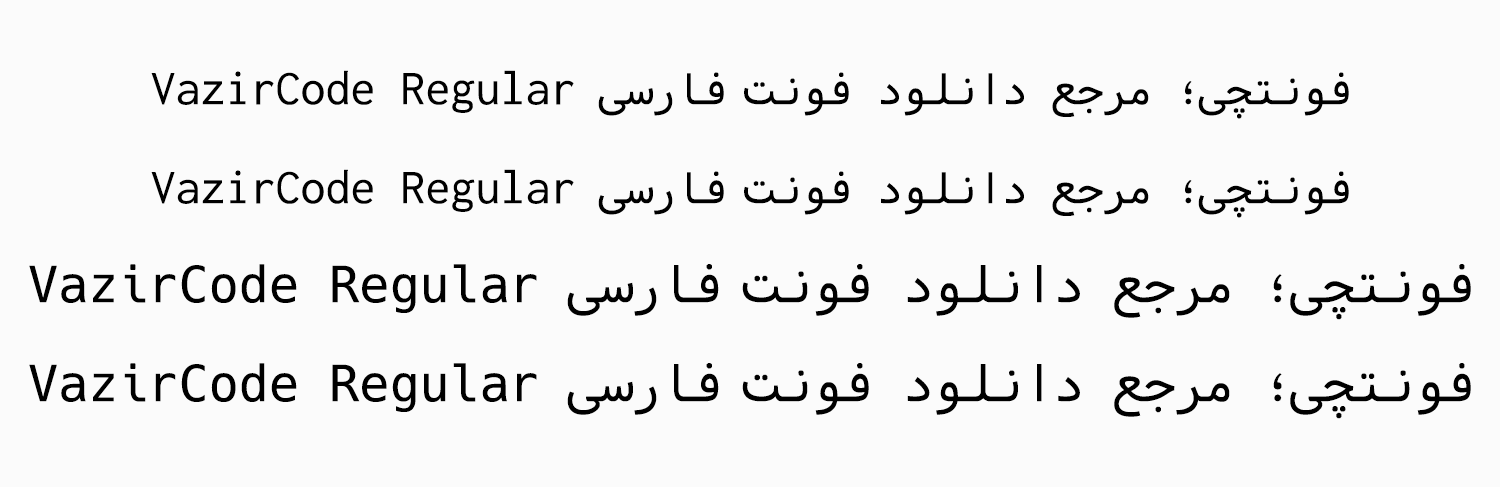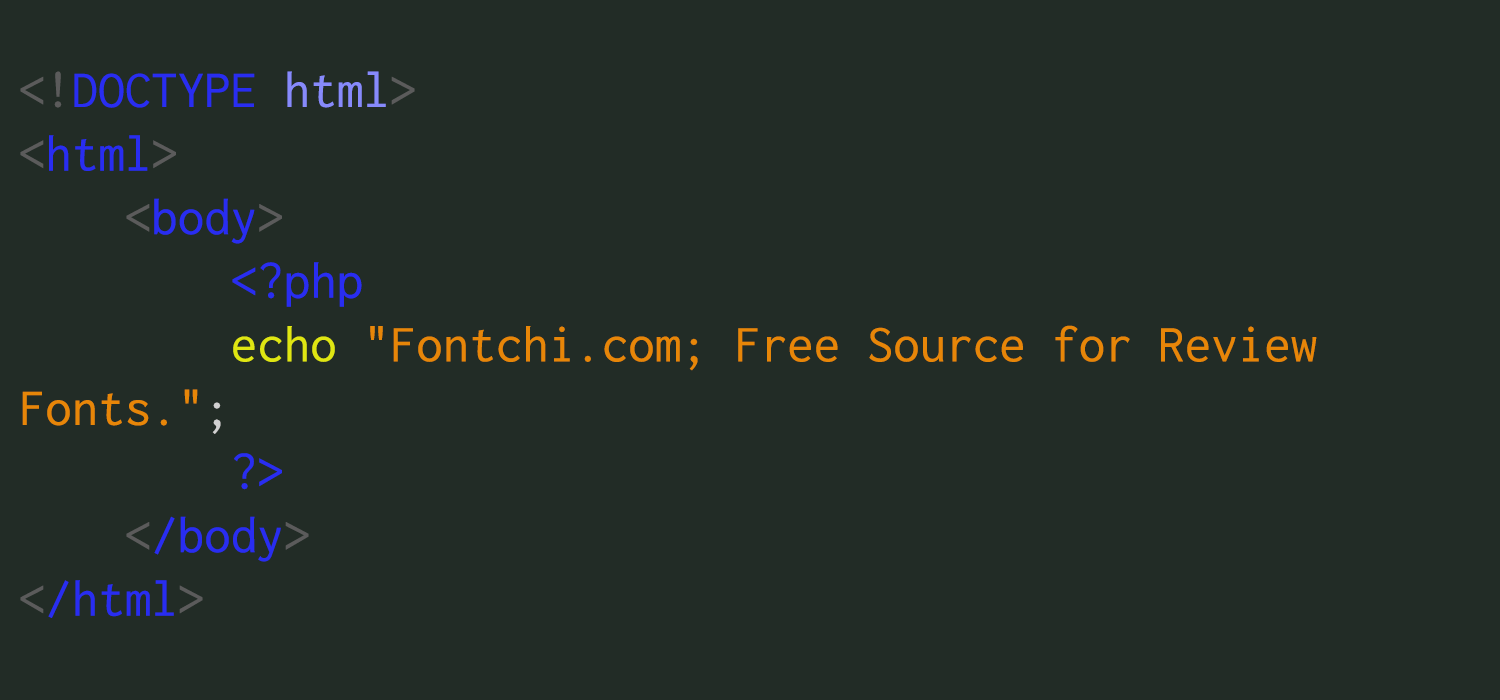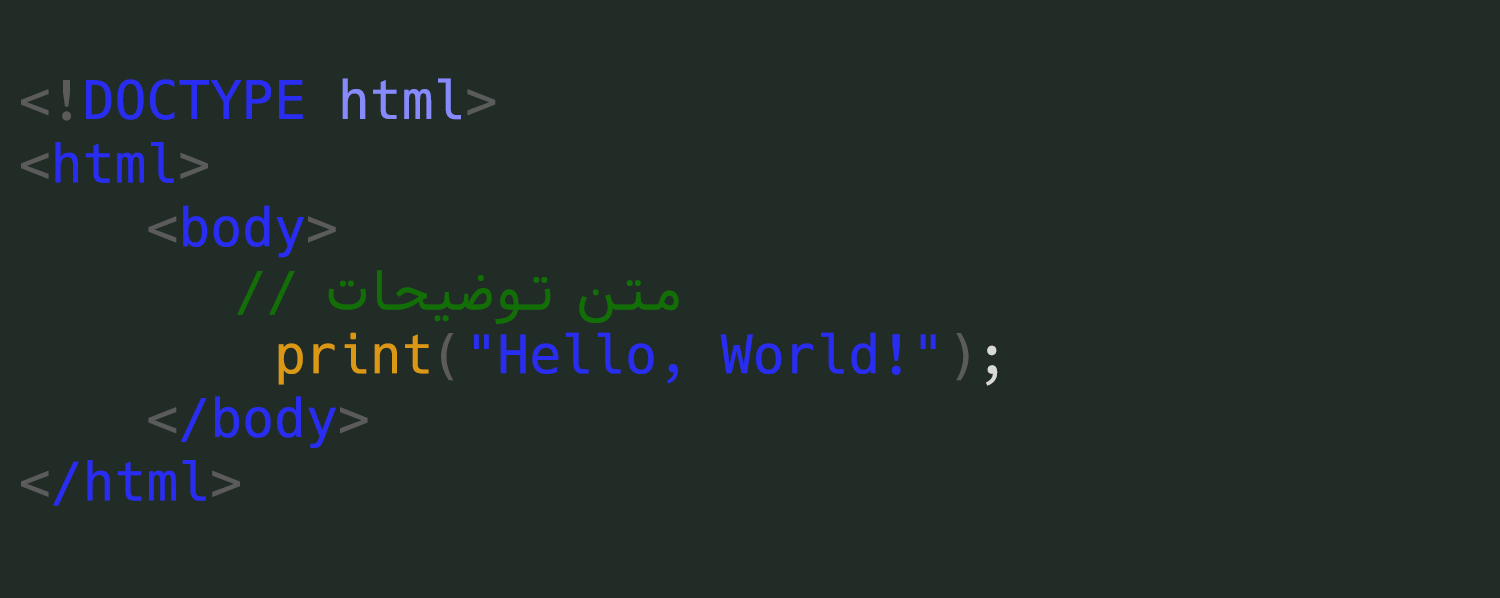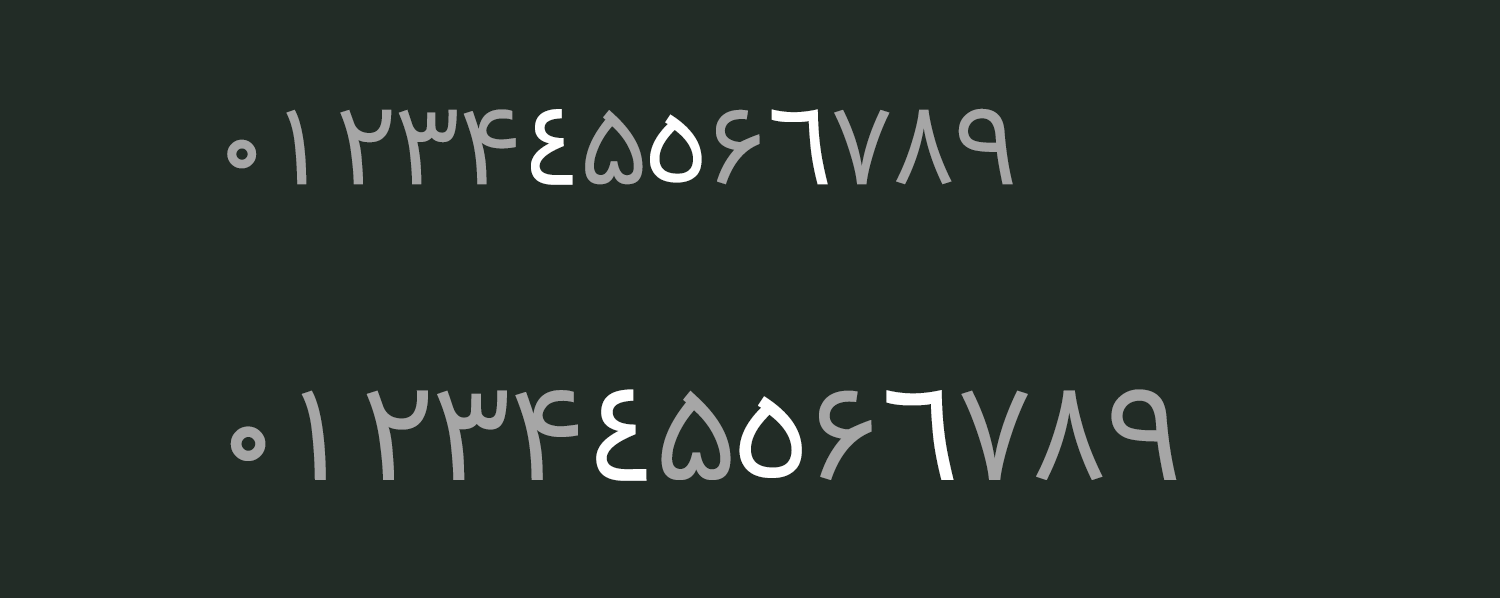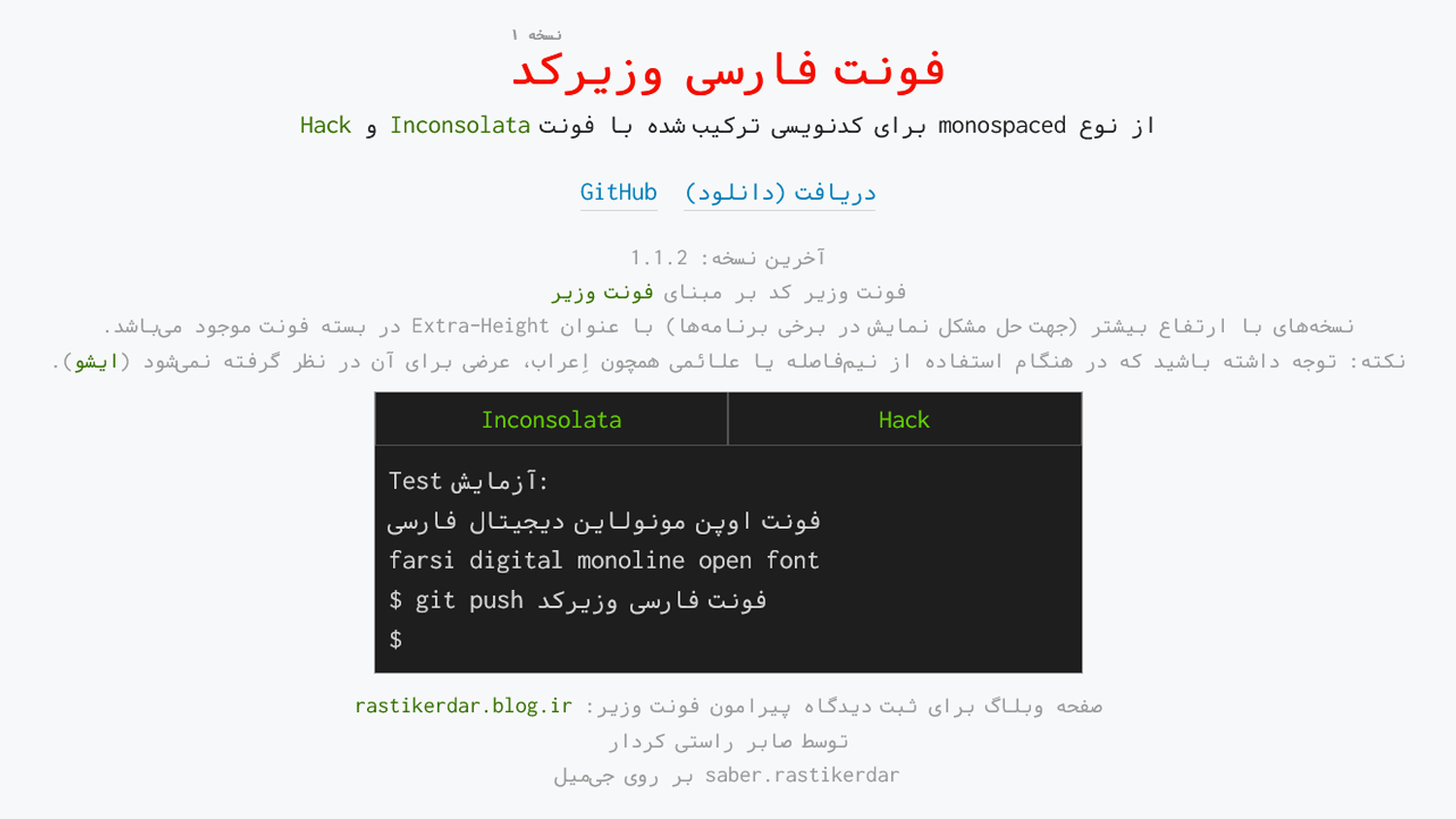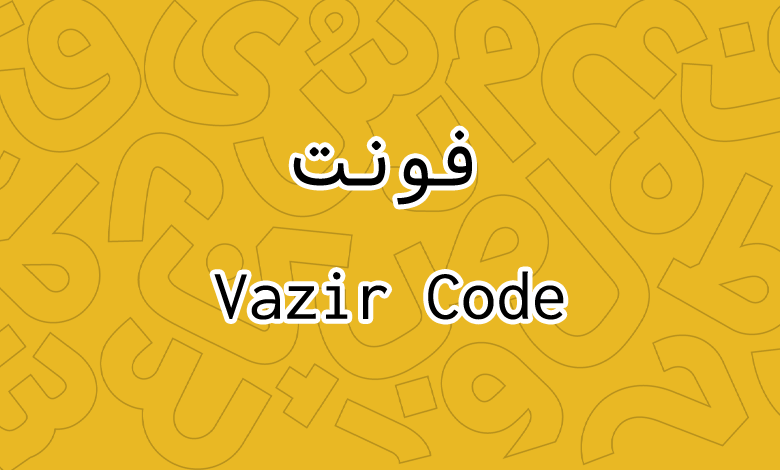
فونت وزیرکد (Vazir Code)
فونت وزیرکد (به انگلیسی: Vazir Code) همانطور که از نامش مشخص است یک فونت مناسب برای برنامه نویسی است. این قلم نیز از دیگر کارهای منتشر شده توسط مرحوم صابر راستی کردار است که یک سال پس از انتشار فونت وزیرمتن طراحی و در دسترس عموم قرار گرفت.
در ادامه این نوشته از سایت فونتچی به نقد و بررسی فونت برنامه نویسی وزیرکد خواهیم پرداخت. قلمی که با نصب آن در سیستم عامل ویندوز، لینوکس یا مک میتوانید از تنظیمات برنامههای مختلفی همچون VsCode گرفته تا سایر برنامههای برنامه نویسی، این فونت را برای پوسته یا تم خود در نظر بگیرید.
بررسی فونت وزیر کد (Vazir Code) برای برنامه نویسی
اگر از زبانهای برنامهنویسی مختلفی همچون زبانهای قدیمی C و جاوا گرفته تا زبانهای PHP و پایتون برای توسعه نرمافزار استفاده میکنید، استفاده از فونت مناسب از اهمیت بالاتری برخوردار است. چرا که ضمن خواناتر کردن کدها، به شما نیز کمک خواهد کرد کدهای خود را بهتر درک کنید.
از همین رو فونت وزیرکد در سال ۱۳۹۵ توسط این طراح با همان سبک فونت وزیر ساخته شد تا کاربران فارسی زبان با خوانایی بهتری اقدام به کدنویسی کنند.
سبک طراحی و وزن فونت وزیرکد
فونت وزیرکد بر مبنای فونت وزیرمتن ساخته شده است. همان شکل و شمایل را برای طراحی حروف فارسی، لاتین و اعداد را دارد. با این تفاوت که ساختار مونواسپیس روی آن اعمال شده است. البته ناگفته نماند که این فونت یک قلم در گروه تایپفیس است که با تلفیقی از دو فونت اپن سورس Inconsolata و Hack در کنار فونت وزیر ایجاد شده است.
این فونت از دو سبک وزنی پشتیبانی میکند. حالت اول که نسخه معمولی آن است و از فونت Inconsolata تبعیت میکند و حالت دوم که بر مبنای فونت Hack طراحی شده است. هر دو سبک فونت، دارای یک نسخه معمولی و یک نسخه با ارتفاع بیشتر با نام Extra Height هستند که به منظور رفع مشکلات نمایشی فونت در برخی برنامهها ایجاد شده است. اگر مشکلی از نظر ارتفاع با فونت داشتید، از حالت با ارتفاع آن استفاده کنید.
پشتیبانی از زبان انگلیسی و فارسی
فونت وزیرکد با اینکه اساس برنامه نویسی در تمام زبانها بر پایه زبان انگلیسی است، اما از زبان فارسی و به تبع، زبان عربی که بر پایه رسمخط فارسی است پشتیبانی میکند.
به لطف این پشتیبانی چند زبانه به سادگی میتوانید از متون فارسی به منظور درج راهنما استفاده کنید یا اگر برنامههای سادهای را کدنویسی خواهید کرد که لزومی به استفاده از فایل زبان ندارند، قادر باشید به راحتی آنها را برنامهنویسی کنید.
پشتیبانی حرفه ای از اعداد فارسی هک شده
این فونت جدای از پشتیبانی اعداد لاتین برای برنامه نویسی دارای نسخه مخصوص اعداد فارسی نیز میباشد. در بسته دانلود فونت وزیرکد یک پوشه مخصوص اعداد فارسی هک شده با نام Farsi-Digits قرار دارد که فایلهای این فونت به اختصار با نام FD نامگذاری شدهاند.
بدین ترتیب اگر ساختار سایت، اپلیکیشن موبایل یا محیطی که قرار است از این فونت در آن استفاده کنید طوری است که لزوما احتیاج به تایپ اعداد فارسی دارید، خبری از اعداد لاتین نیست. لذا با قرار داشتن صفحه کلید روی هر زبان فارسی یا غیرفارسی لاتین، حتی وقتی از اعداد بخش ماشین حساب صفحه کلید استفاده کنید، اعداد فارسی تایپ خواهند شد.
مناسب برای تمام زبان های برنامه نویسی
این فونت از تمامی زبانهای برنامه نویسی پشتیبانی میکند. از زبانهای ساده HTML گرفته تا کدهای CSS که وظیفه زیباسازی را دارند تا زبانهای برنامه نویسی PHP و پایتون را به سادگی میتوانید با این قلم برنامه نویسی کنید.
سبک طراحی فونت برنامه نویسی وزیر کد طوری است که یک فونت بر اساس سبک فونتهای فارسی را برآورده کرده است تا برنامه نویسان فارسی زبان، در یک محیط با خط فونت مناسب کدهای برنامه نویسی خود را توسعه دهند.
استفاده از فونت مناسب در برنامه نویسی اهمیت بسیار فراوانی دارد. خصوصا زمانی که برای حل برخی چالشهای برنامهنویسی ساعتها ممکن است بر روی توابع و کدهای برنامه نویسی کار کنید. جدای از این بسیاری برنامه نویسان از تمهای تاریک برای برنامهنویسی استفاده میکنند که خیره شدن طولانی با چنین ساختار تمی، نیازمند فونت مناسب است که آسیب زیادی به چشمها وارد نگردد.
زیرا با ریز بودن یا لاغر بودن فونت، خواندن برخی کدها در چنین شرایط چالشبرانگیزی سخت خواهد بود و برخی از روی عادت برای تمرکز بهتر ممکن است فاصله مناسب را حفظ نکنند یا اینکه با تغییر در میزان باز کردن چشمان خود، جدایی از مشکلات بینایی، چین و چروک زیادی را در ناحیه چشم و پیشانی ایجاد کنند.